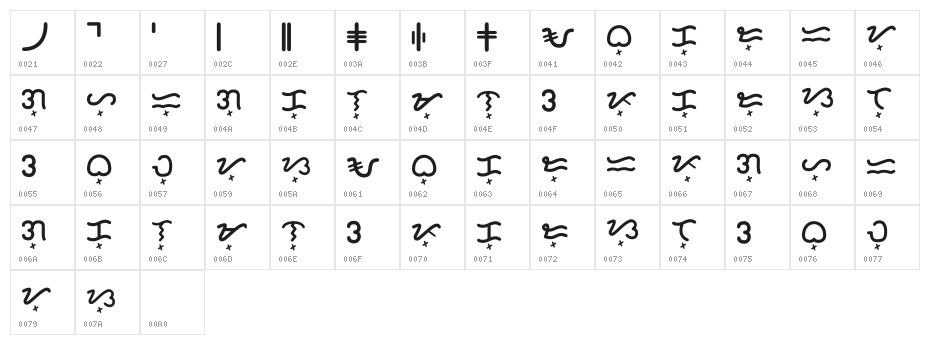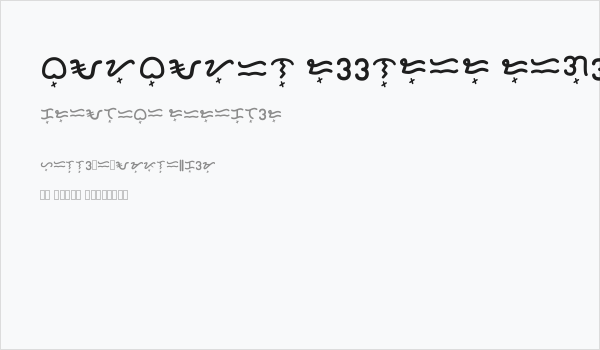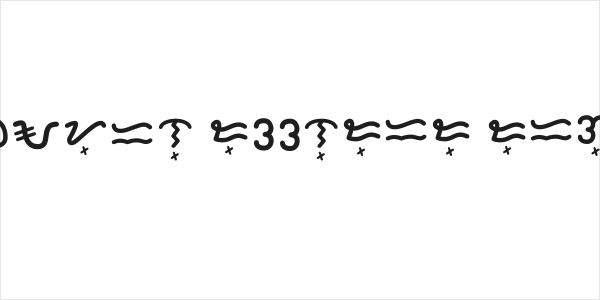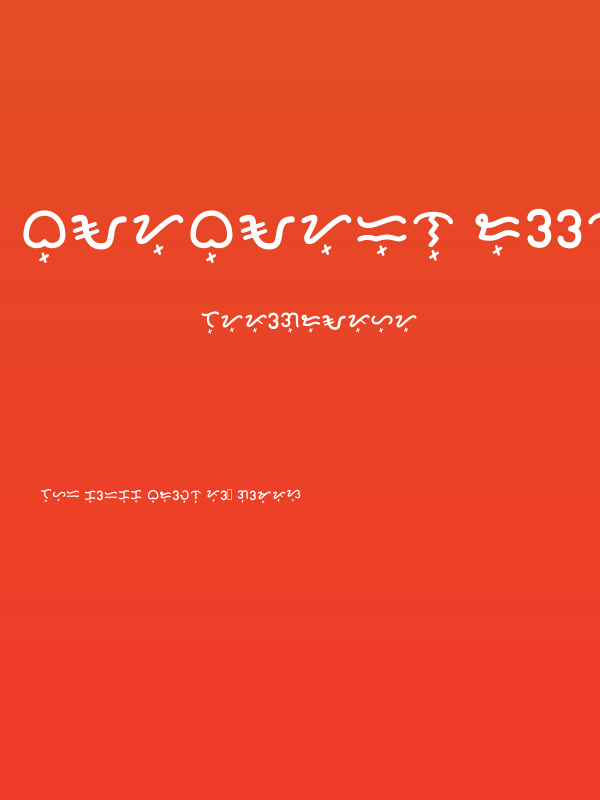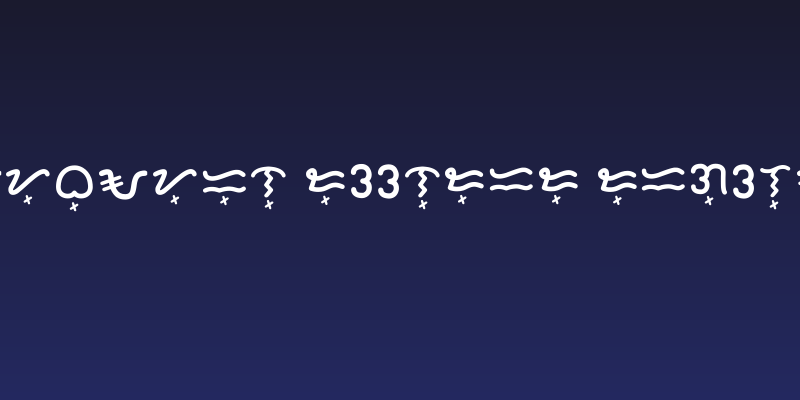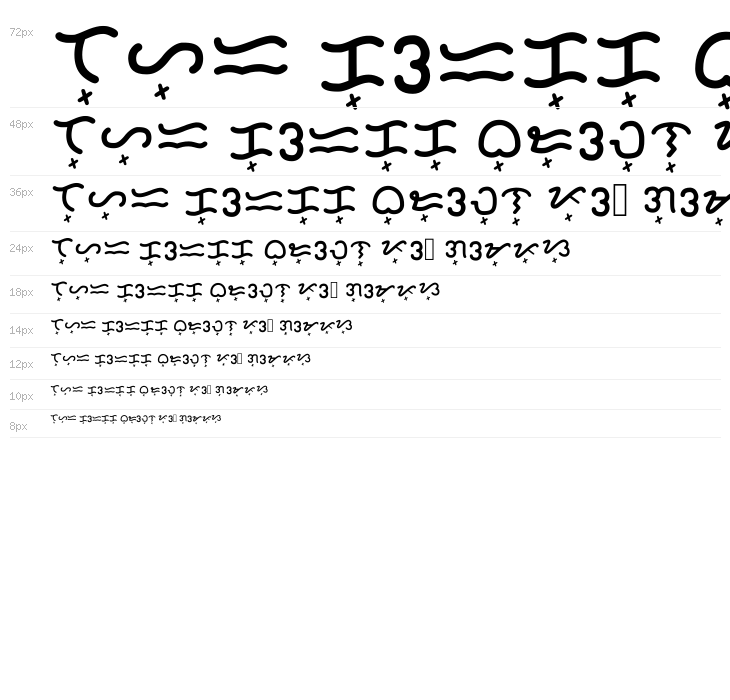
Baybayin Rounded Regular Font
| Caso d'uso | Logos, Educational materials, Cultural projects |
| Progetti proposti | Ideal for cultural projects, educational materials, branding, and digital content that celebrates Filipino heritage. |